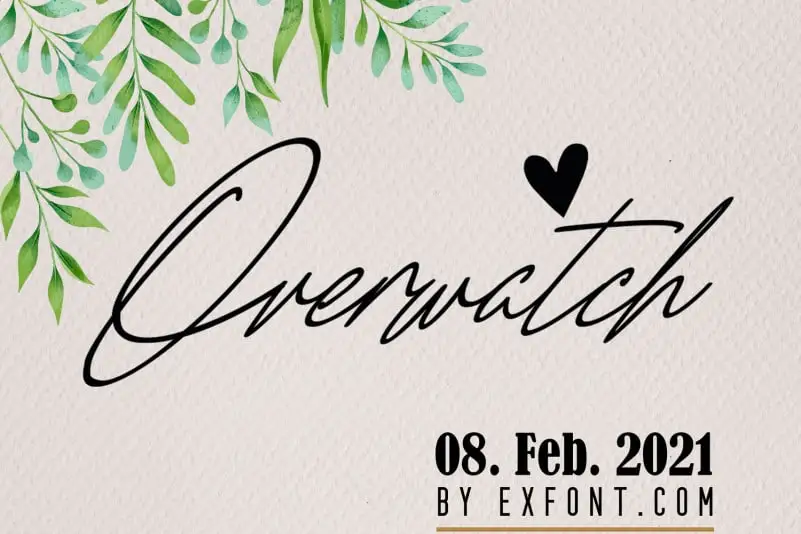
Overwatch Signature Font – Download Grátis
A Overwatch Signature Font é uma fonte escrita à mão sem linhas com estilo casual-chic perfeito para diversos usos. Seu traçado livre e elegante faz dela uma escolha ideal para branding, convites de casamento e cartões personalizados, possivelmente até como fonte para rótulos de vinho. Este é um recurso visual que traz à vida os estilos criativos da Overwatch, com seus tons suaves e linhas fluidas, tornando-a uma opção perfeita para aqueles buscando um toque único e sofisticado em seu design gráfico. A fonte é criada pelo designer exfont, garantindo a qualidade que espera de um recurso que combina elegância com versatilidade.